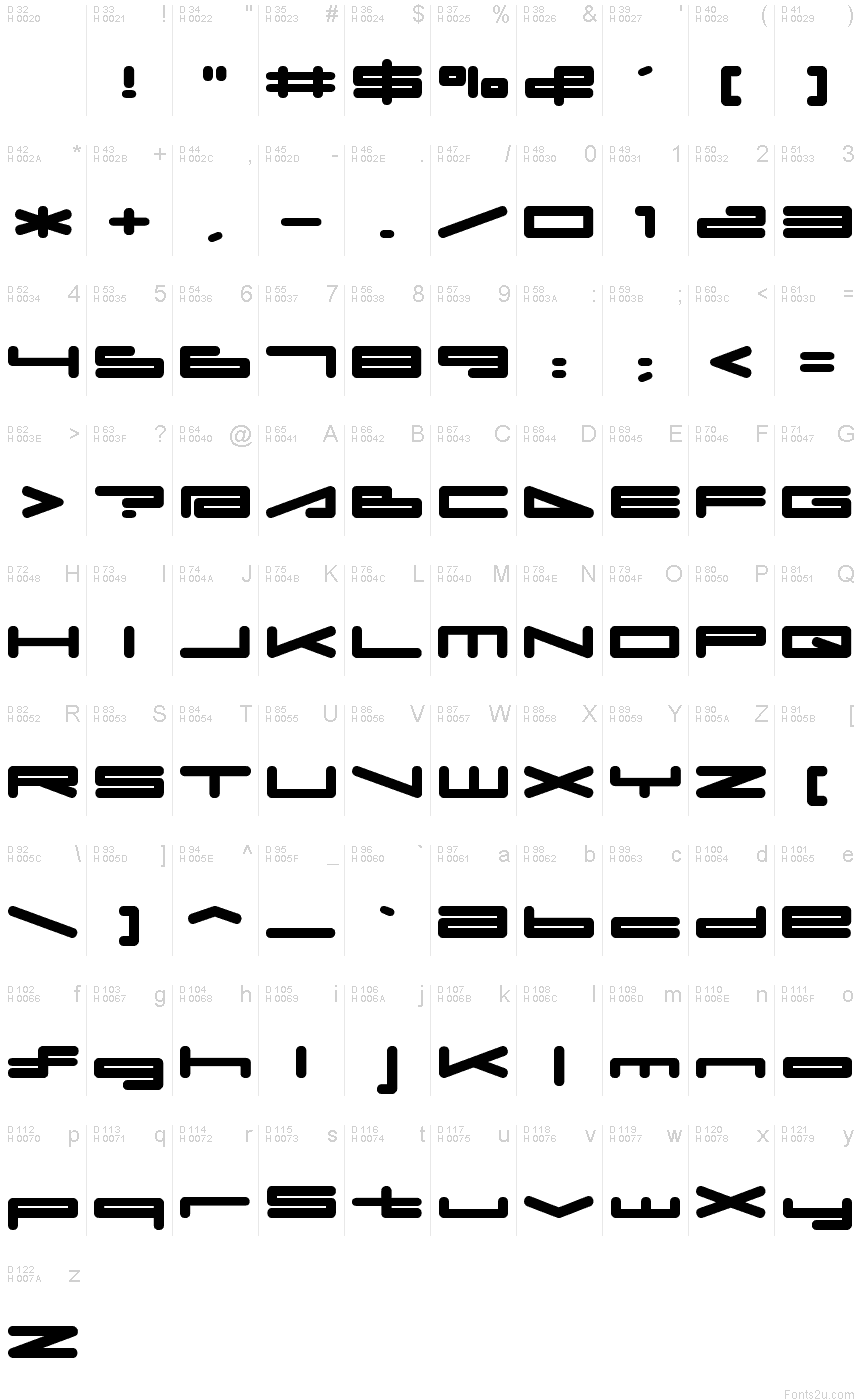
Umop, darmowy font techno typu display, ma futurystyczny, nisko osadzony charakter, zbudowany z grubych, zaokrąglonych słupków i łagodnych, prostokątnych zakrętów. Litery są modularne, niemal przypominające rurki, z długimi poziomymi liniami, przyciętymi wewnętrznymi prześwitami i okazjonalnymi pionowymi spadkami, co nadaje krojowi osobliwy, maszynowy rytm.
Naturalnie pasuje do ulotek muzyki elektronicznej, tytułów gier indie, brandingu aplikacji, nagłówków plakatów i okładek sci-fi, gdzie krótki znak graficzny musi wyglądać syntetycznie, ale nie krucho. Jako darmowy font, szczególnie dobrze sprawdza się w logo, planszach tytułowych i kompaktowych nagłówkach, ponieważ te szerokie kształty sprawiają, że nawet kilka liter wygląda graficznie i stanowi spójną całość.